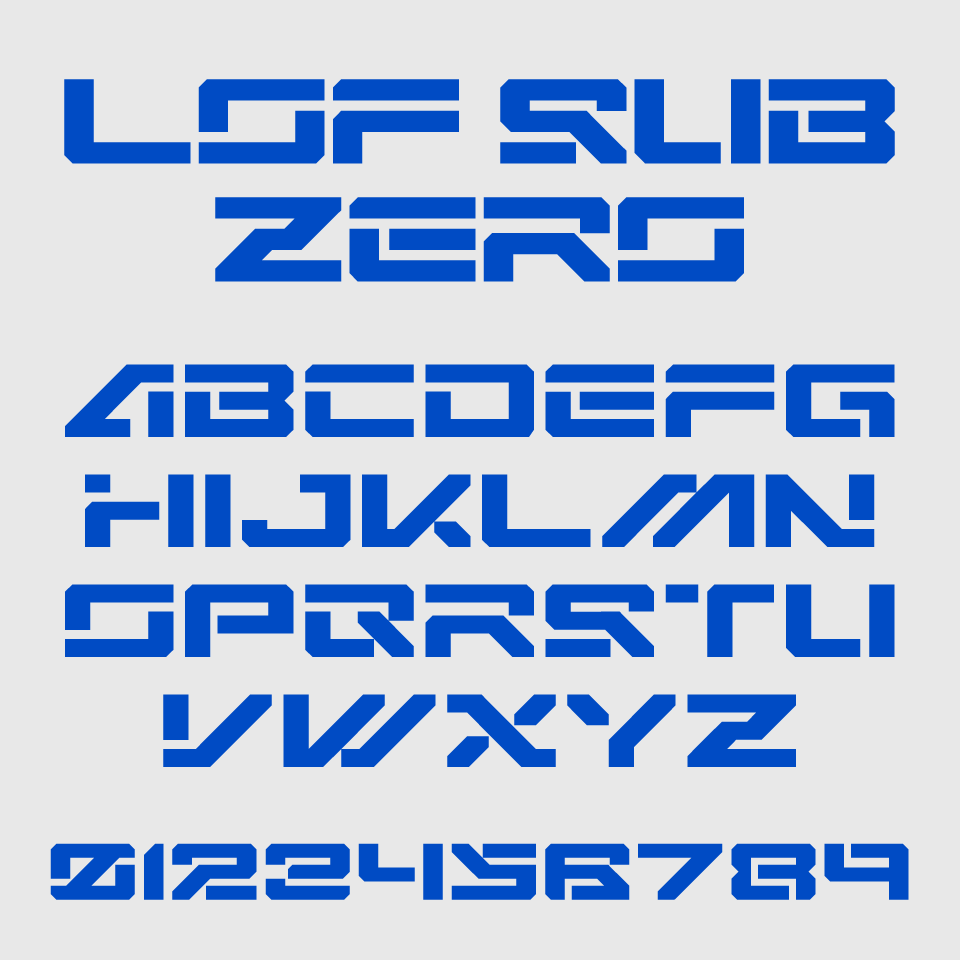
LOF Sub Zeroフォントは、メカニカルで近未来的なムードを持つデザインフォントです。
角ばった形状と直線的な構成が、金属のような無機質で機械的な印象を与えます。特に斜めのラインや一部切り欠いたような文字設計が、ロボティックな世界観を強調しており、SF映画のタイトルやゲームUIにもぴったりです。
力強く重厚感がありながら、どこか制御された冷たさを感じるデザインが魅力です。